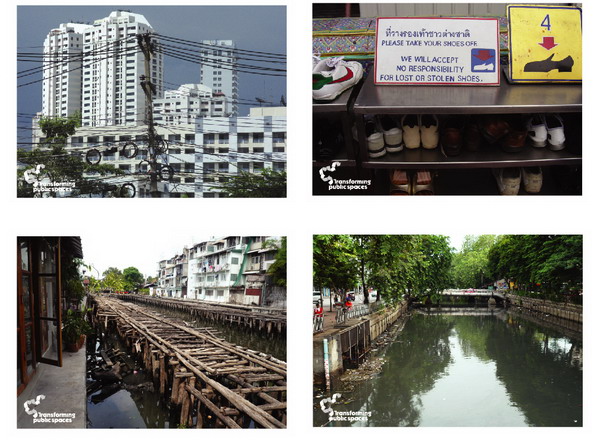
Bangkok Design Festival 2008
3.Typography Documentary สารคดีสั้นเรื่อง "ตื้นลึกหนาบางของตัวพิมพ์ตะกั่ว (ไทย)"
โดยอ.ประชา สุวีรานนท์ และอ.ชัยยศ อิษฎ์วรพันธุ์วันที่ 19-20 ตุลาคม 2551 ที่บ้านจิม ทอมป์สัน
หนังจะถูกแบ่งออกเป็นหนังสั้นประมาณ 10 เรื่อง เรื่องละประมาณ 5-10 นาที แบ่งเป็น 5 กลุ่ม โดยจะเป็นการสำรวจในแง่มุมต่างๆ อย่างในกลุ่มแรกจะเป็นข้อมูลประวัติศาสตร์ กระบวนการคิดค้นของเจมส์ โลว์ , บรัดเล และฝรั่งเศส ซึ่งเป็น 3 ตัวพิมพ์ในยุคตั้งไข่ นอกจากนั้นก็จะมี "อัมพวา" ประวัติศาสตร์มีชีวิตของตัวตะกั่ว กลุ่มที่ 2 เป็นเรื่องความงามที่เกิดจากสัมผัสและแรงกด กลุ่มที่ 3 นำเสนอกายภาพของตัวพิมพ์ตะกั่ว เช่น ขนาดและสัดส่วน ที่เป็นมรดกสู่ตัวพิมพ์ดิจิทัล ซึ่งจะมีการตั้งคำถามย้อนกลับไปว่า การพิมพ์ตะกั่วคืออะไร ในกลุ่มที่ 4 จะเป็นเรื่องความตื่นเต้นในวันหวยออก จากโต๊ะเรียงถึง 4 แยก กลุ่มสุดท้ายคือ ลมหายใจของตัวตะกั่ว โดยจะนำเสนอเรื่องราวของโรงหล่อ "รุ่งเรืองอักษร" ซึ่งเป็นโรงหล่อโรงสุดท้าย
5.Maywa Denki   14-26 ตุลาคม ที่หอศิลป์กทม
ย้อนไปเมื่อปีค.ศ. 1960 ณ ประเทศญี่ปุ่น Sakaichi Tasa ดำรงตำแหน่งแชร์แมนของบริษัท Maywa Denki ของเขาเองซึ่งเป็นธุรกิจทางอากาศยานและผลิตยุทโธปกรณ์ในช่วงสงครามโลกครั้งที่ 2 อีก 10 ปีต่อมาหลังสงครามยุติ Maywa Denki ก็ขยับตัวขึ้นเป็นบริษัทขนาดกลางที่รับผลิตชิ้นส่วนอุปกรณ์ต่างๆให้กับบริษัทยักษ์ใหญ่ของญี่ปุ่นอย่าง Toshiba , Matsushita มีพนักงานกว่า 100 ชีวิต กิจการกำลังรุ่งเรืองไปได้ด้วยดี แต่ทว่า ในปี 1979 Maywa Denki ก็ต้องผจญชะตากรรมเดียวกันกับอีกหลายร้อยบริษัท ที่ต้องปิดกิจการลงไปเนื่องจากพิษเศรษฐกิจจากผันผวนของราคาน้ำมันในกลุ่มโอเปก ซึ่งเป็นวิกฤตการที่สะเทือนใจชาวโลกเป็นยิ่งนัก
14 ปีต่อมา Masamichi และ Nobumichi ลูกชายทั้งสองของ Sakaichi Tasa ก็เริ่มต้นรื้อฟื้น Maywa Denki อีกครั้ง โดยใช้ชื่อเดิม แต่ไม่ได้ทำกิจการผลิตชิ้นส่วนเครื่องใช้ไฟฟ้าเพื่อขายเหมือนเดิม แต่กลับลงทุนผลิตอุปกรณ์เหล่านั้นเพื่อการแสดง!
Maywa Denki เริ่มต้นอีกครั้งในปี 1993 และใช้เวลาไม่นานก็เรียกเสียงฮือฮาให้กับผู้ชมชาวญี่ปุ่น สมาชิกในวงจะเรียกเครื่องดนตรีทุกชิ้นว่าเป็น "ผลิตภัณฑ์" และเรียกการแสดงทุกครั้งว่าเป็นการ "สาธิตผลิตภัณฑ์" โดยจะอยู่ในรูปแบบที่ไม่จำกัด เช่น นิทรรศการ คอนเสิร์ต การแสดงสด งานเพลง งานวิดีโอ งานเขียน ฯลฯ ยูนิฟอร์มที่ใส่ก็เป็นชุดของพนักงานในโรงงานเดิมเพื่อสะท้อนให้เห็นถึงช่วงเวลาที่ดีที่สุดของบริษัทรวมไปถึงอุทิศให้กับกิจการขนาดกลางที่ขับเคลื่อนญี่ปุ่นให้เจริญรุดหน้าอาณาประเทศหลังสงคราม ถึงแม้ว่าผลิตภัณฑ์ที่พวกเขาออกแบบนั้นไม่สามารถนิยามได้ว่ามันคืออะไร แต่ทุกครั้งที่กลไกเดินเครื่องทำงาน เชื่อได้เลยว่า ไม่มีใครเคยเห็นอะไรแบบนี้มาก่อนแน่นอน ไม่เชื่อลองพิมพ์ชื่อพวกเขาใน google ดูสิ
ปล.งานนี้ Maywa Denki อาจจะยังไม่ได้มาแสดงด้วยตนเอง แต่จะส่งผลิตภัณฑ์มาให้ชมกันก่อน
6.Transforming Public Spaces : Change Bangkok 14-26 ตุลาคม 2551 ที่หอศิลป์กทม.
Transforming Public Spaces เป็นกิจกรรมลำดับที่สองภายใต้โครงการ Creative Cities ที่กรุงเทพมหานครร่วมมือกับ British Council โดยต้องการเน้นถึงบทบาทของศิลปินที่มีผลต่อการเปลี่ยนแปลงของเมือง ซึ่งจะเปิดโอกาสให้คนทั่วไปได้มีส่วนร่วมในการเปลี่ยนแปลงเมือง โดยเริ่มจากเมืองหลวงอย่างกรุงเทพฯก่อน ภายใต้ชื่อโครงการ Change Bangkok : กรุงเทพฯ หัวเป็นหาง จากคำถามง่ายๆ คุณคิดว่าพื้นที่ไหนของกรุงเทพที่ควรปรับปรุง? อาจจะเป็นที่รกร้าง ตึกเก่า ถนน ซอยตัน ที่ทิ้งขยะ หรือสถานที่สาธารณะที่ไม่มีใครเหลียวแล จากนั้นก็ถ่ายรูปสถานที่นั้นส่งเข้ามาในเว็บไซต์ www.changebangkok.com พร้อมคำอธิบายและไอเดียที่อยากให้เปลี่ยน จากนั้นจะมีการโหวตคัดเลือก 10 สุดยอดสถานที่ควรปรับปรุงของกรุงเทพฯ เพื่อมาจัดแสดงเป็นส่วนหนึ่งของนิทรรศการในงานเทศการออกแบบบางกอก 2551